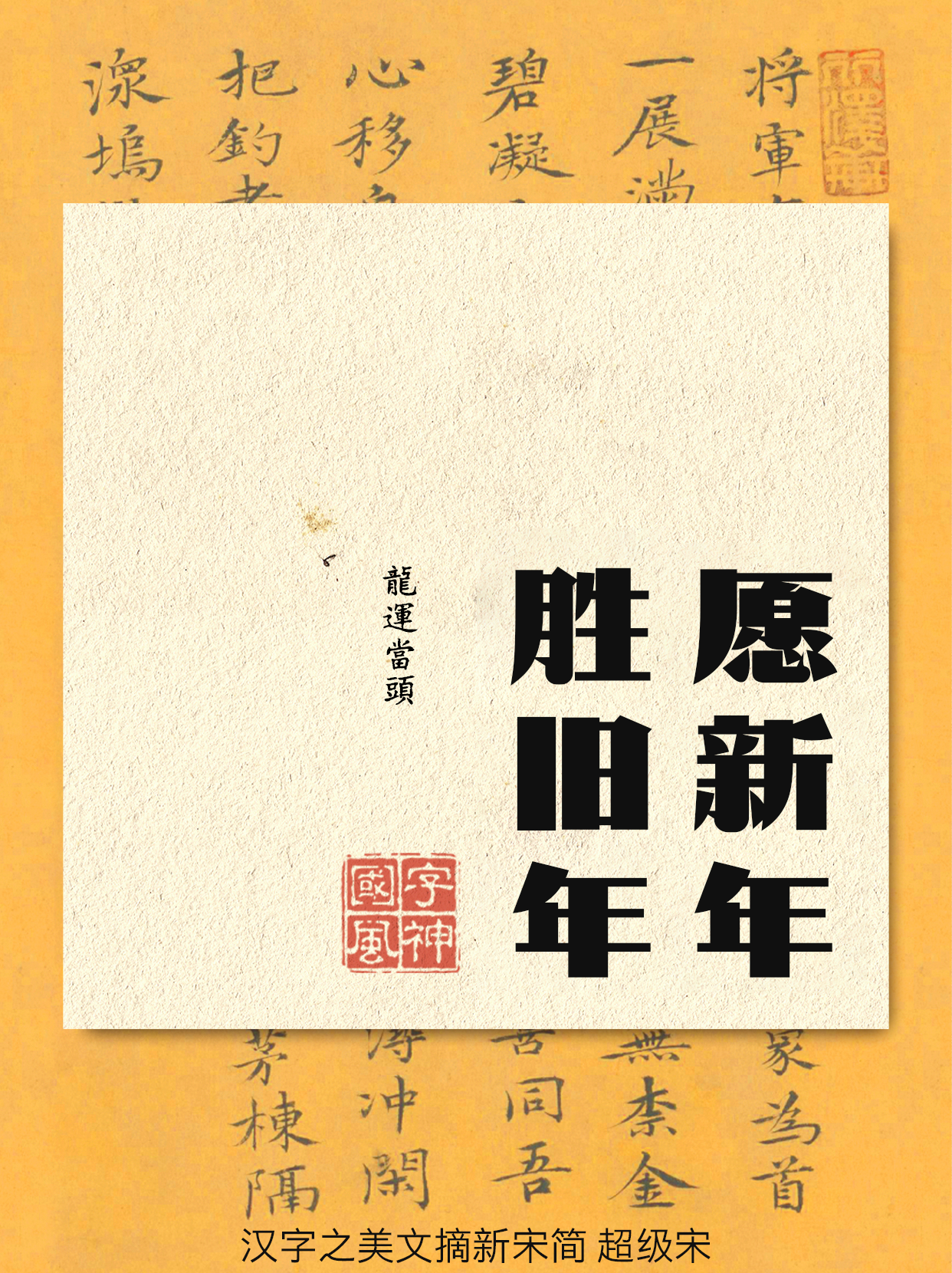
汉字之美文摘新宋简 超级宋
整体规整简洁、空间均匀、重心平稳,字面宽扁,结构严谨、中宫较大。字形复古与现代完美相融合。
横笔画没有任何装饰特点,简洁明快,提笔、捺笔、钩笔画加入圆角的处理方式使笔画更圆润,更带有复古的宋体特点。整体笔画饱满,横细竖粗,弧度大小根据笔画空间进行变化,笔画疏密均匀。视觉更加统一。